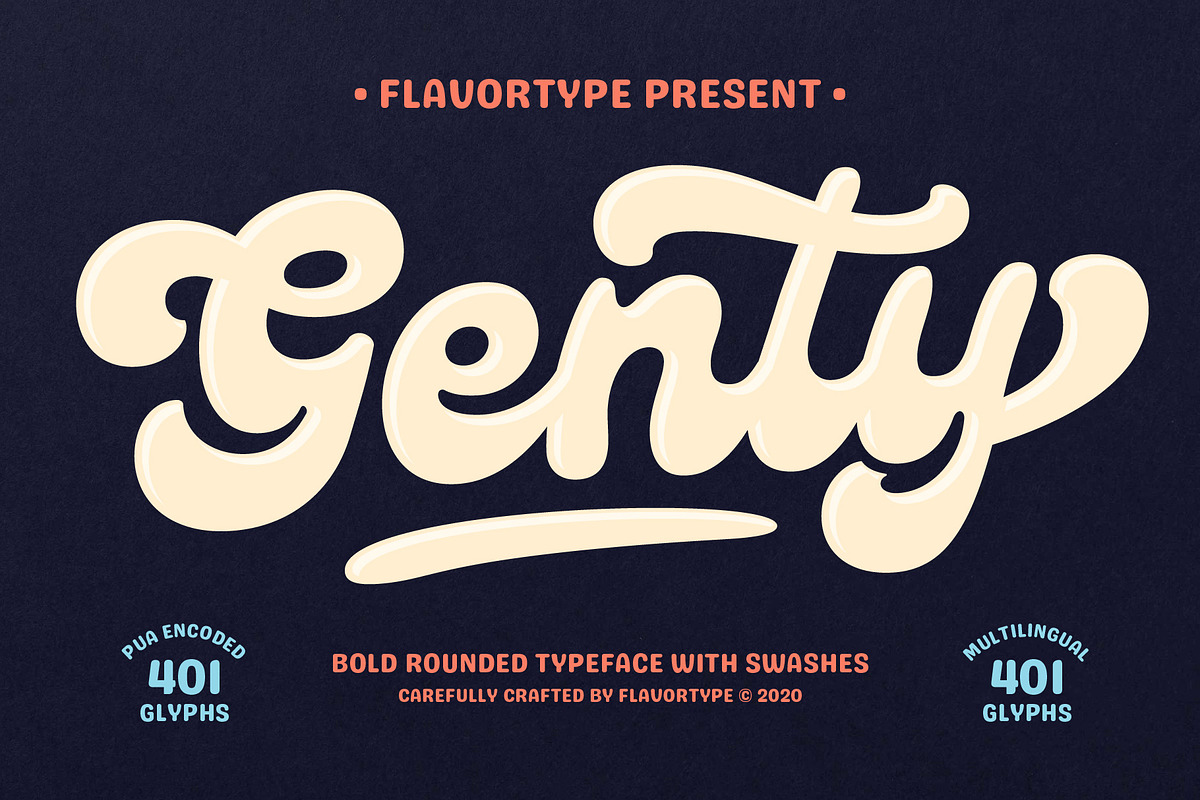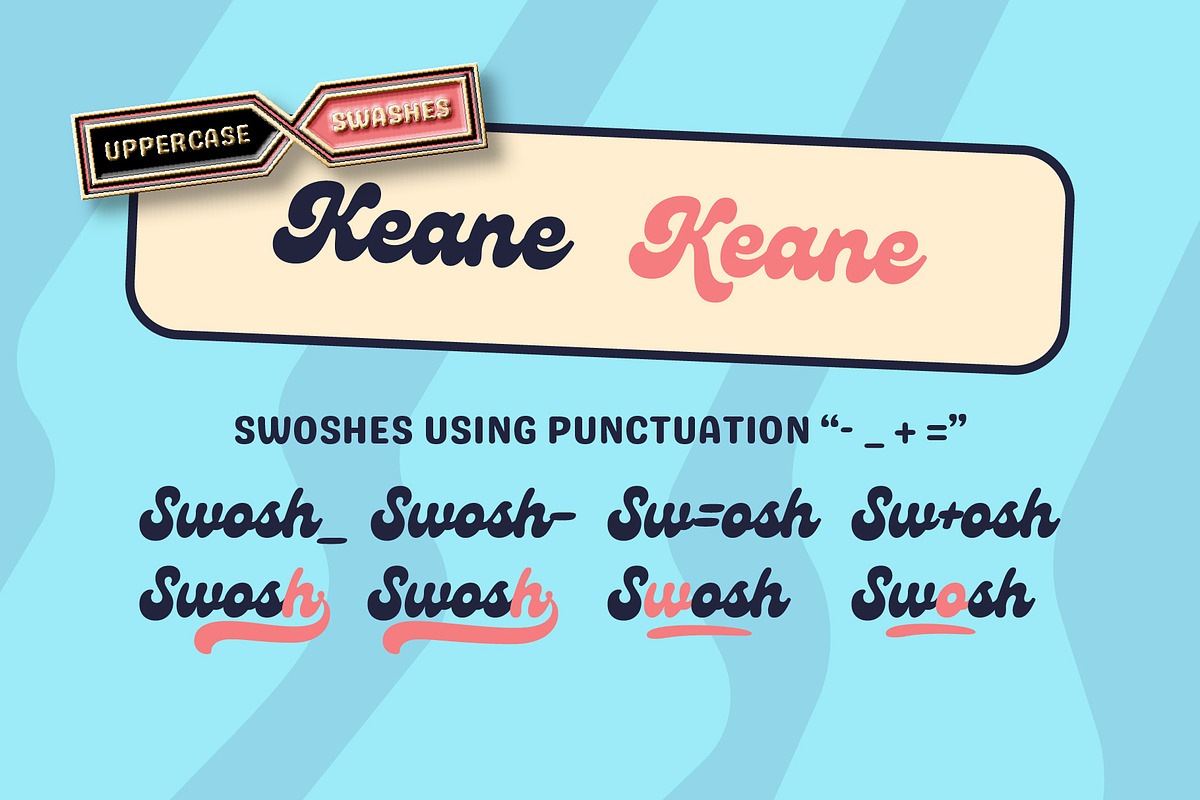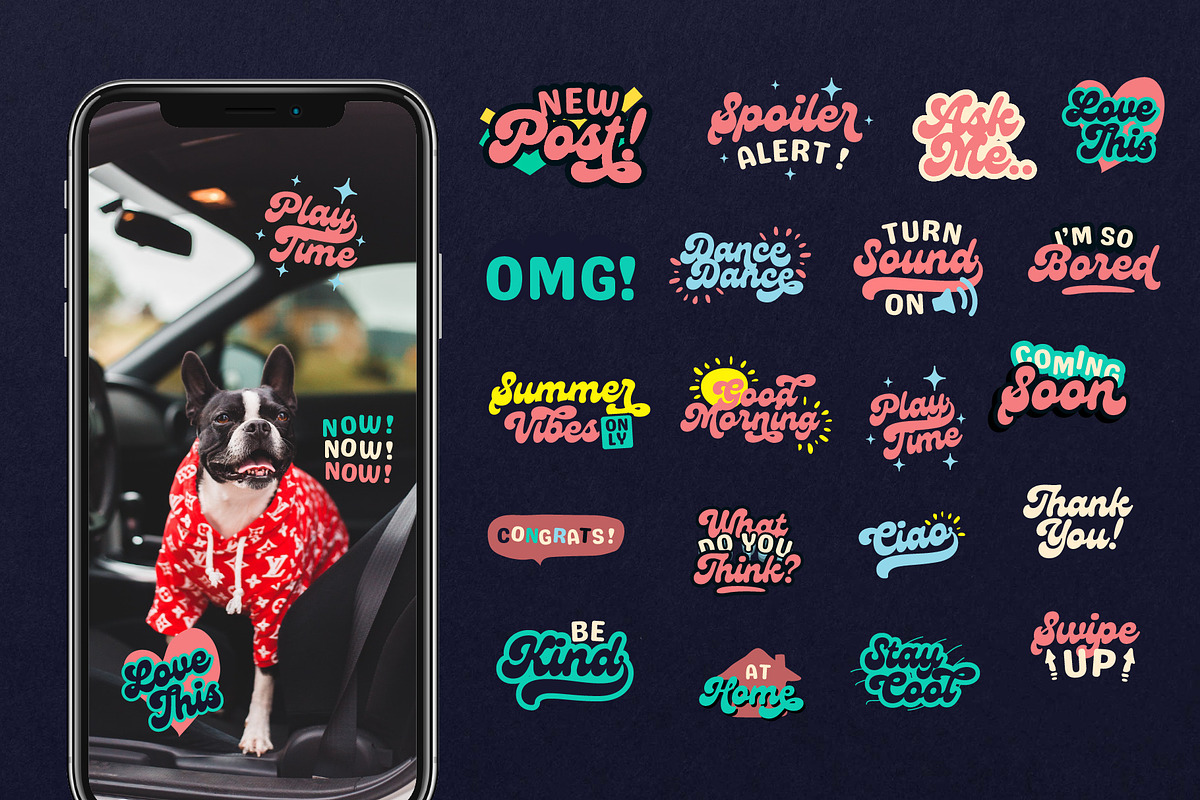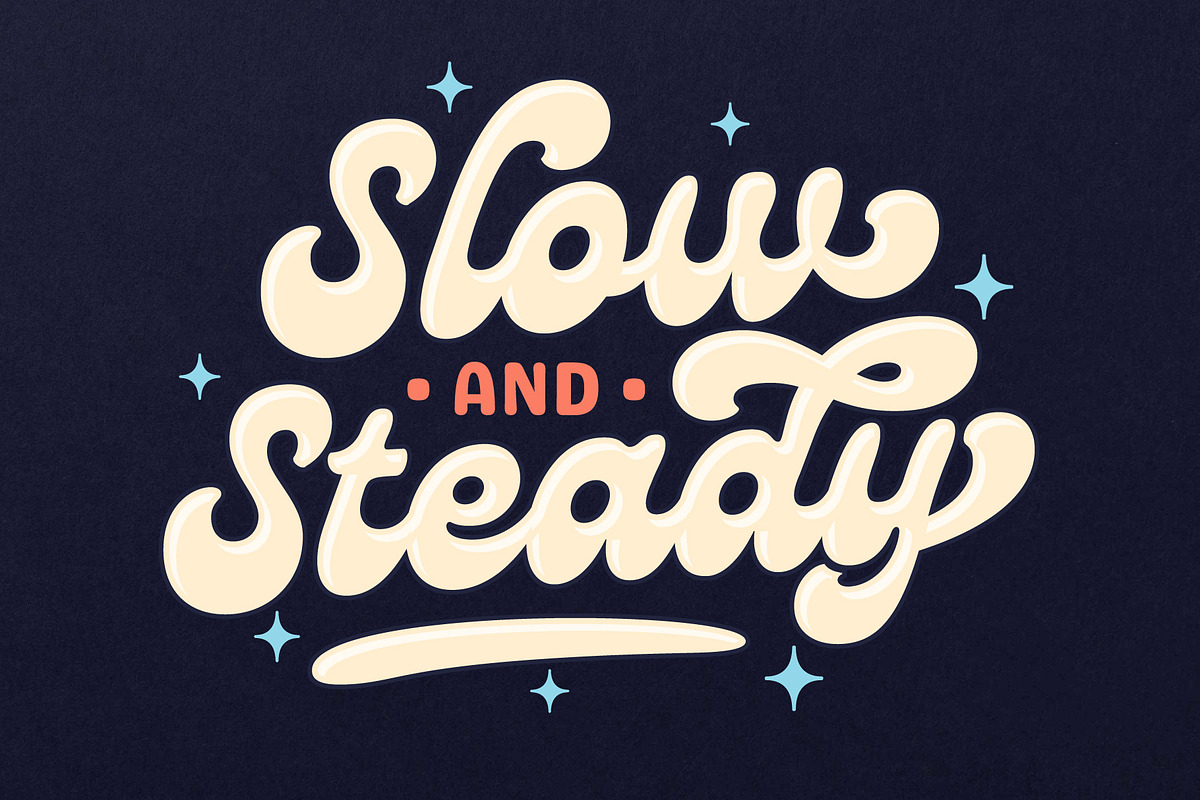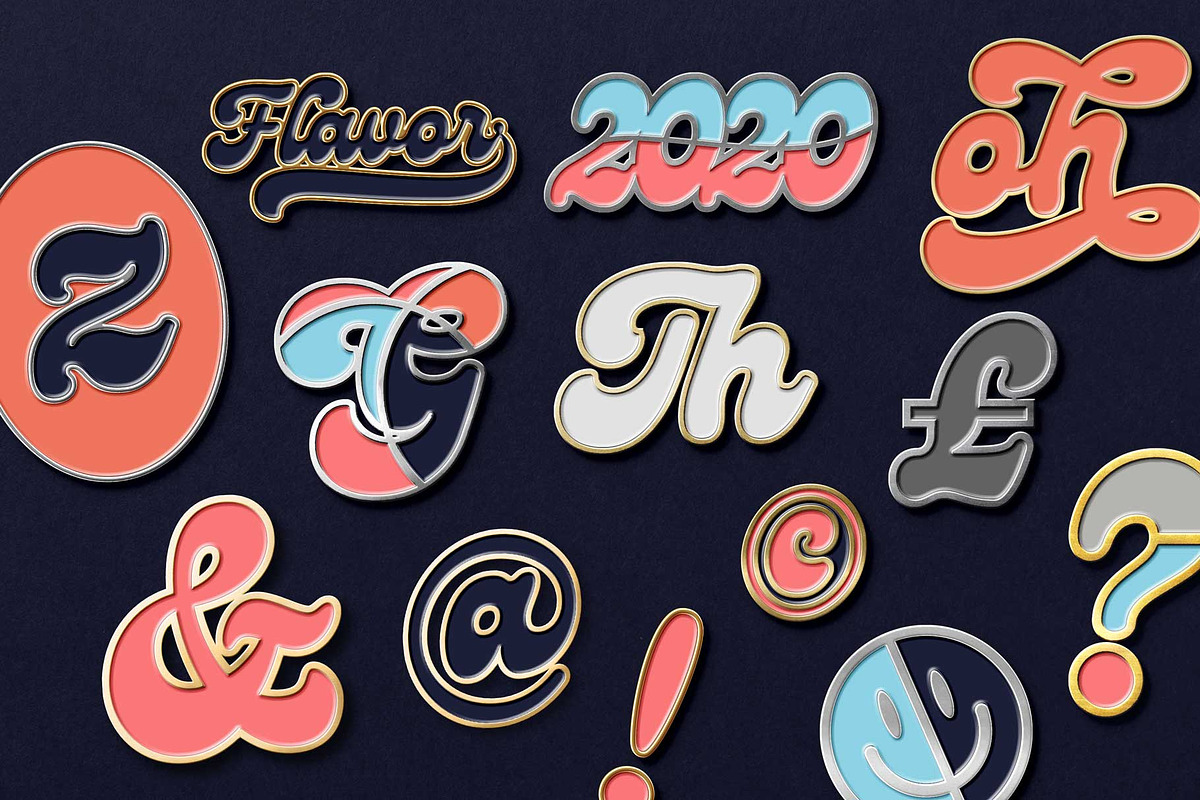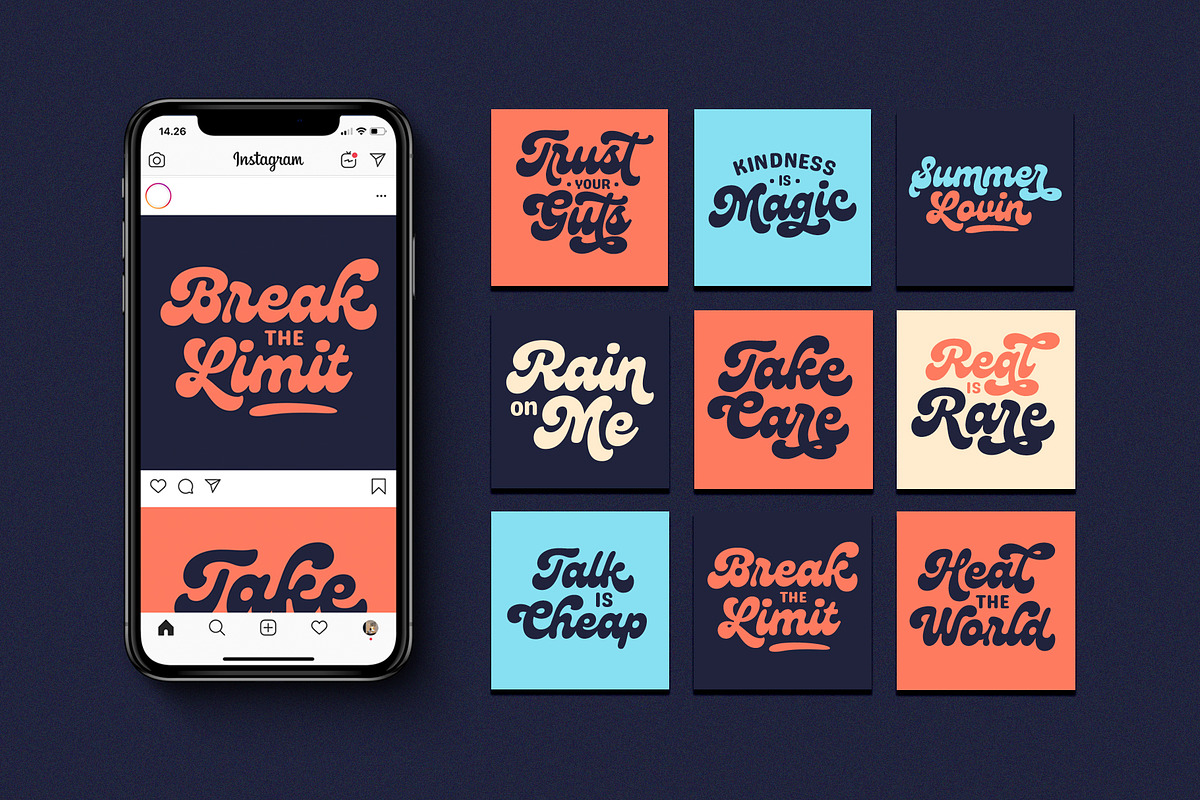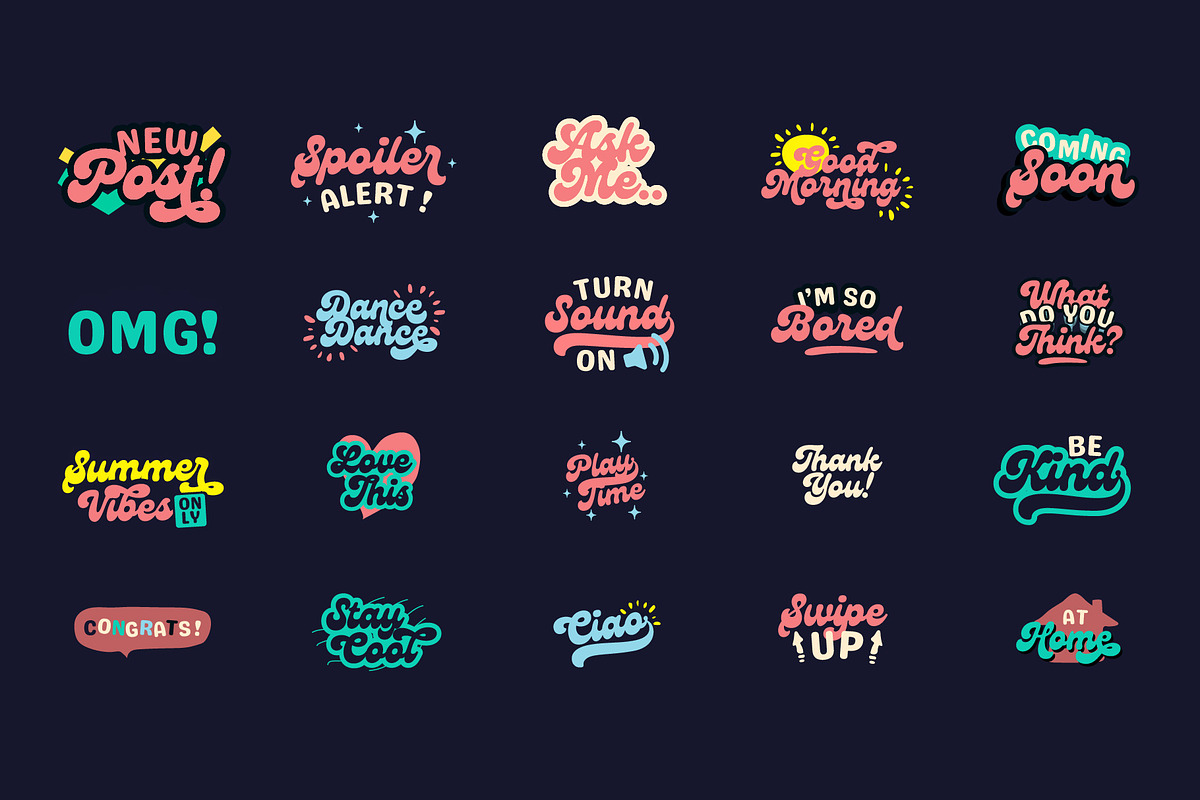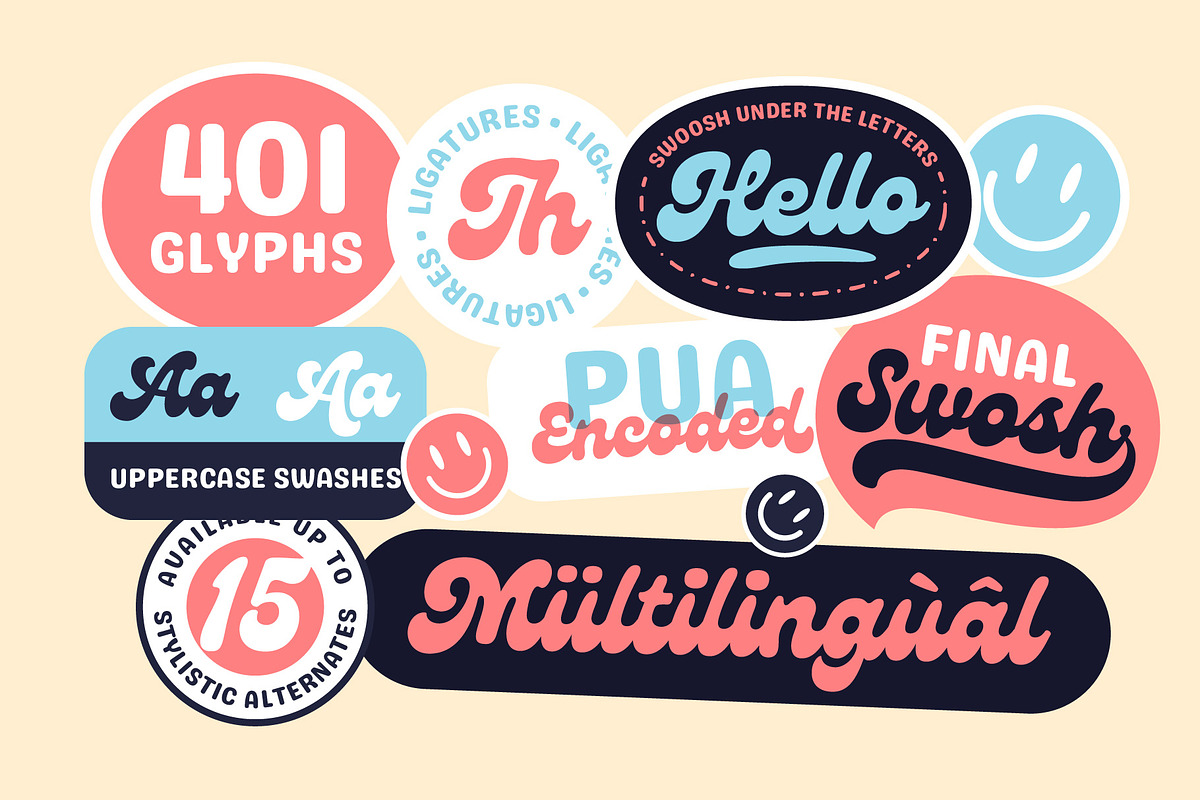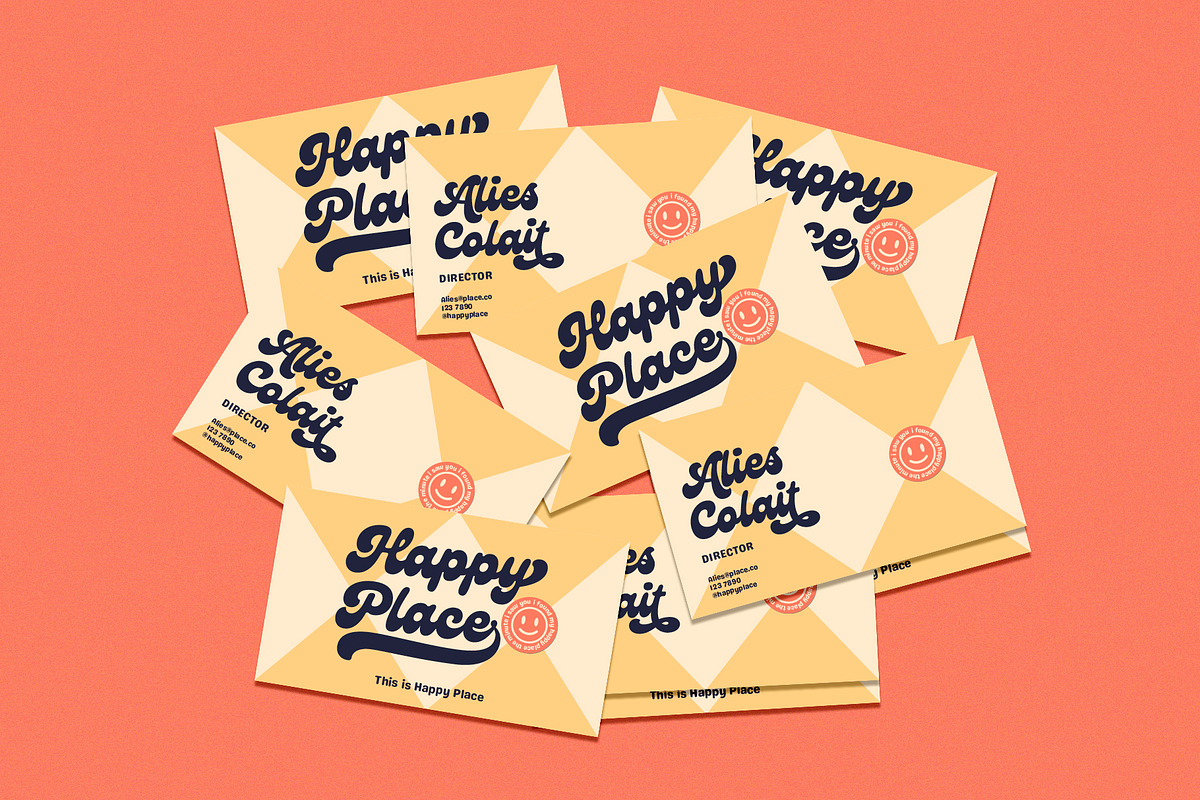
Genty – Bold Rounded Typeface
Genty – Font Script Bold & Rounded yang Penuh Gaya dan Swash Menawan
Kenalkan Genty, jenis huruf script bold yang ceria, modern, dan kaya gaya! Terinspirasi dari kombinasi dua font populer kami sebelumnya—Budge dan Glaw—Genty hadir sebagai versi yang lebih fun, lebih trendi, dan lebih penuh semangat.
Dengan desain bulat tebal, aksen swash elegan, dan nuansa cute nan memikat, Genty cocok untuk berbagai gaya desain: mulai dari branding yang elegan, tampilan media sosial yang playful, hingga kemasan produk yang menonjol.
✨ Fitur Unggulan Genty:
• OpenType lengkap dengan:
• Swash karakter atas & bawah
• Alternatif karakter hingga 15 gaya berbeda
• Ligatur, contextual alternates, stylistic sets
• Uppercase swash, dan efek “swoosh” unik di awal dan akhir huruf
• Semua glyph alternatif dikurasi secara teliti agar tetap menjaga karakter asli font
• Bonus font sans-serif pendamping: Genty Sans, ideal untuk pasangan font serasi
Cocok Digunakan Untuk:
Logo, header, branding, majalah, menu makanan, poster, packaging, dan konten media sosial. Genty memberikan sentuhan yang fleksibel namun tetap mencuri perhatian.
Tampilkan kreativitas Anda dengan Genty – font yang tak hanya cantik, tapi juga penuh gaya dan energi!